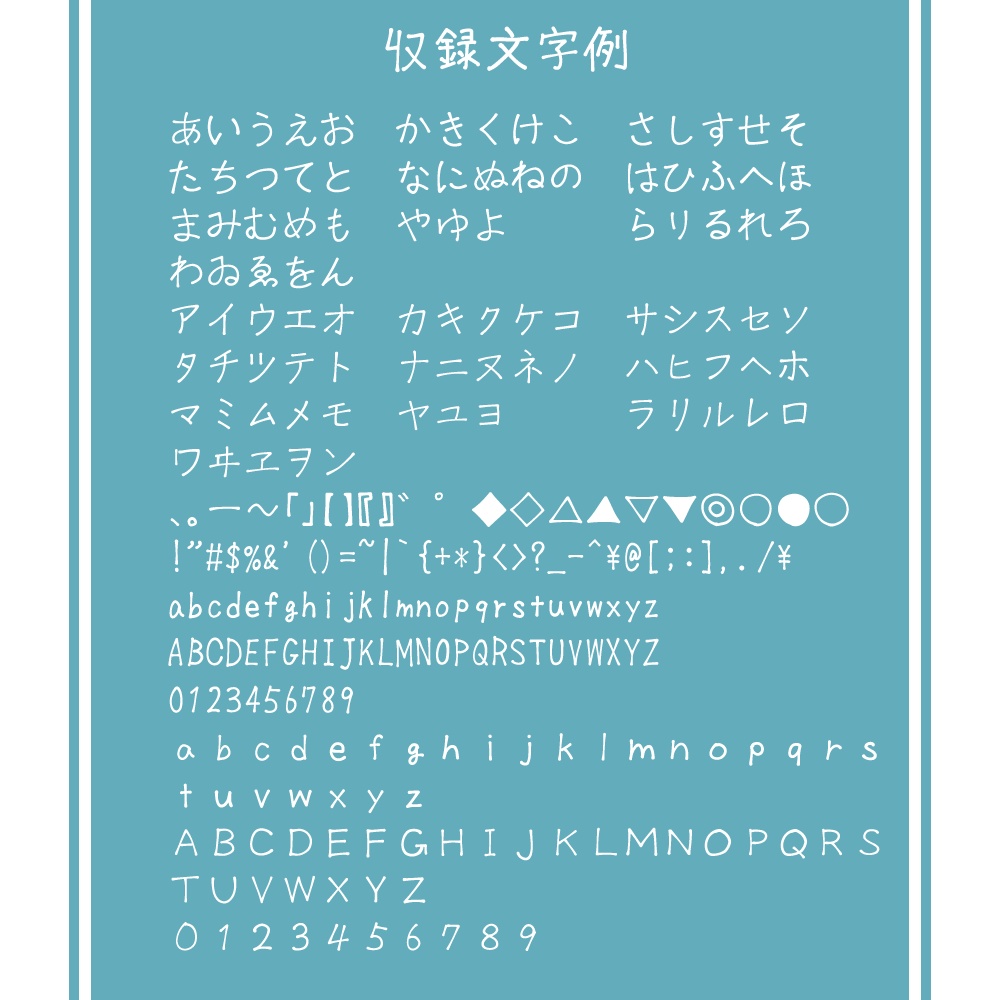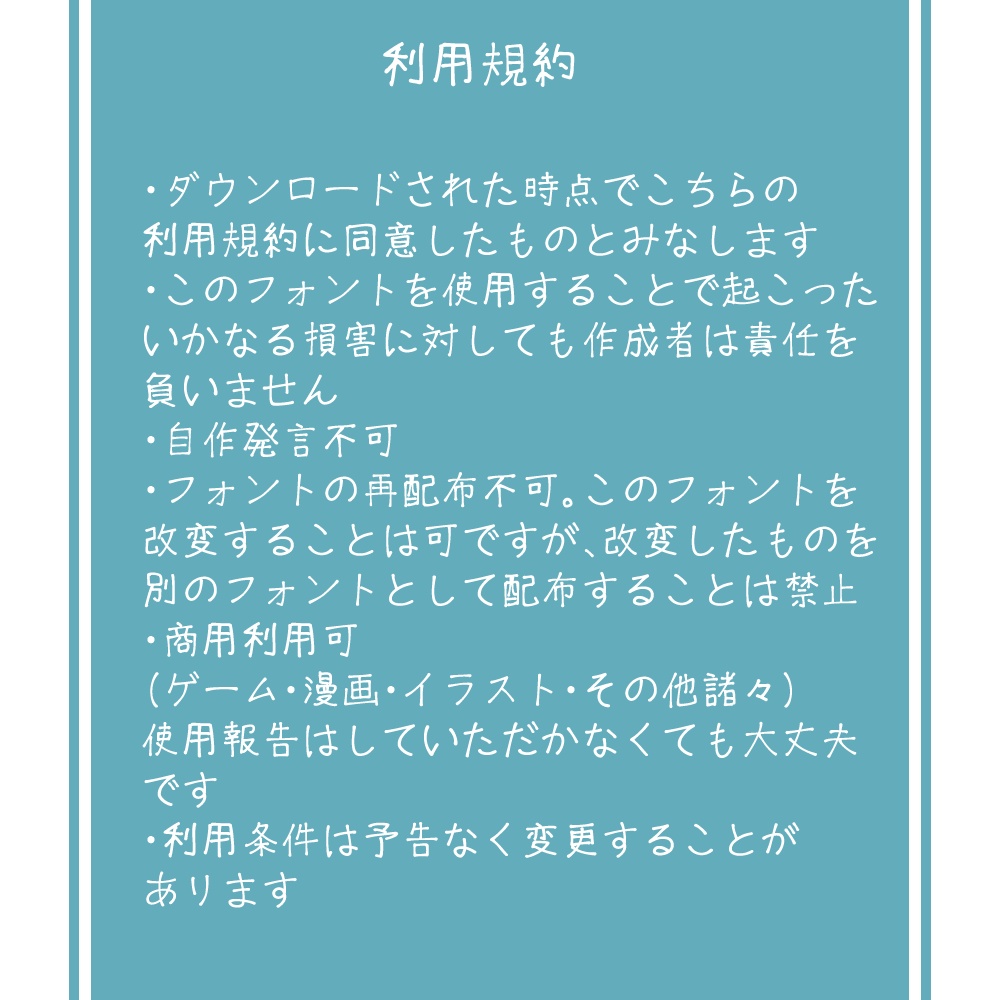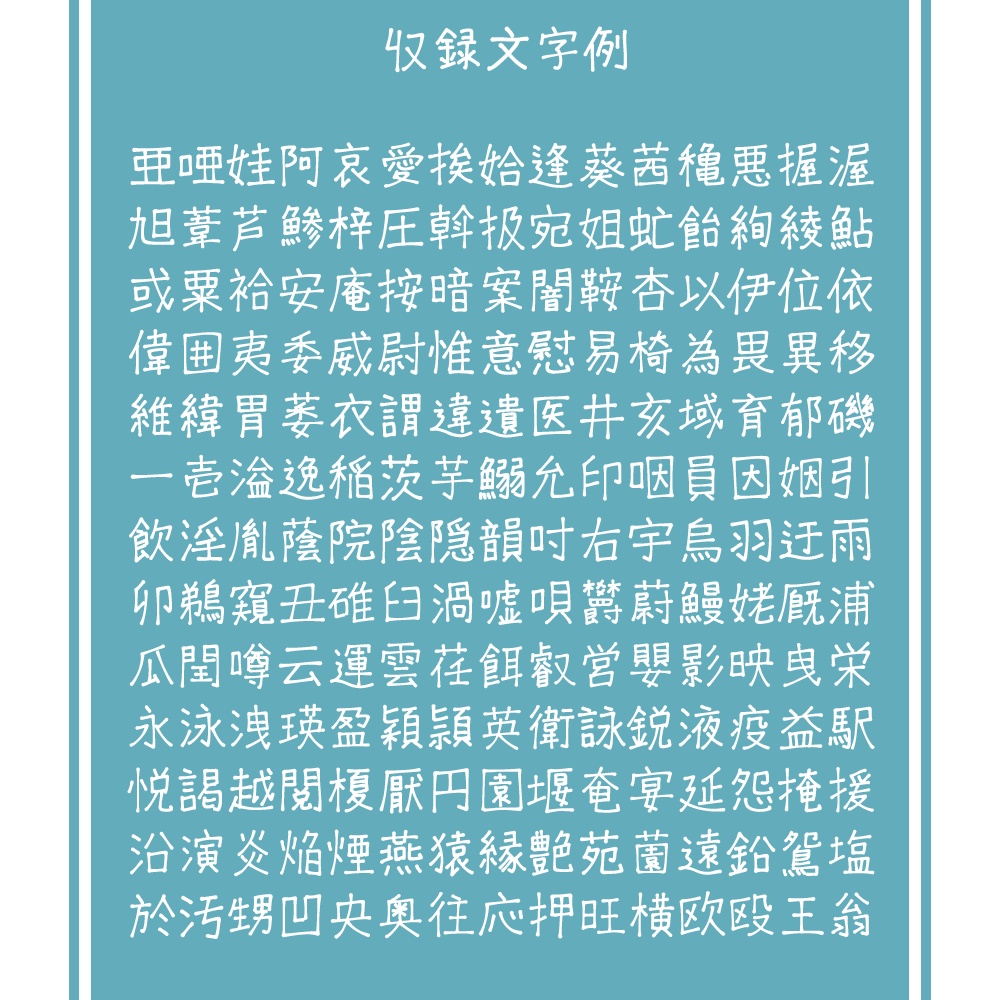
なぜミリペンフォント
ミリペン風の、ちょっと雑な手書きフォントです。 ひらがな、カタカナ、英語、記号、JIS第1水準とJIS第2水準の一部を収録しています。 利用規約を読んでからダウンロードしてください 利用規約 ・ダウンロードされた時点でこちらの利用規約に同意したものとみなします ・このフォントを使用することで起こった、いかなる損害に対しても作成者は責任を負いません ・自作発言不可 ・フォントの再配布不可。このフォントを改変することは可ですが、改変したものを別のフォントとして配布することはやめてください ・商用利用可。使用報告はしていただかなくても大丈夫です ・利用条件は予告なく変更することがあります 本ファイルは武蔵システム(https://opentype.jp/)のTTEditを使って作成しました。